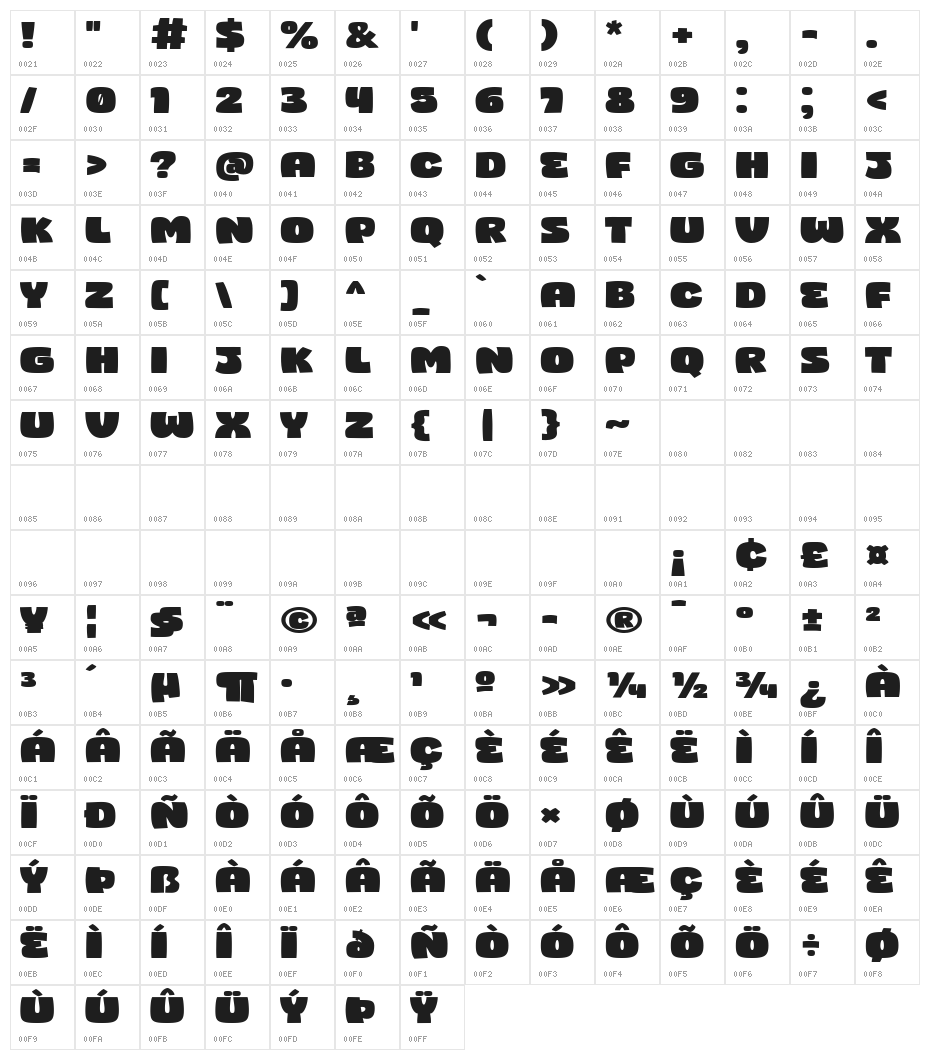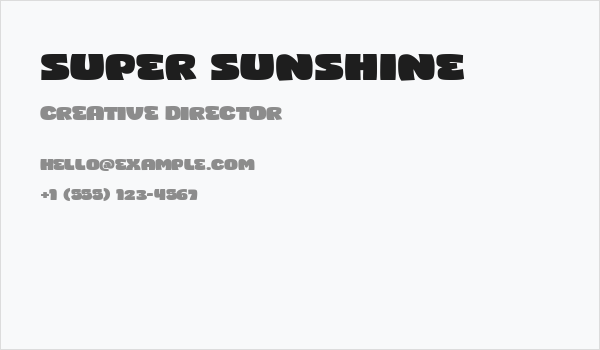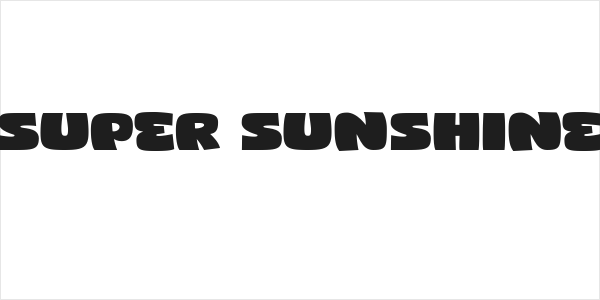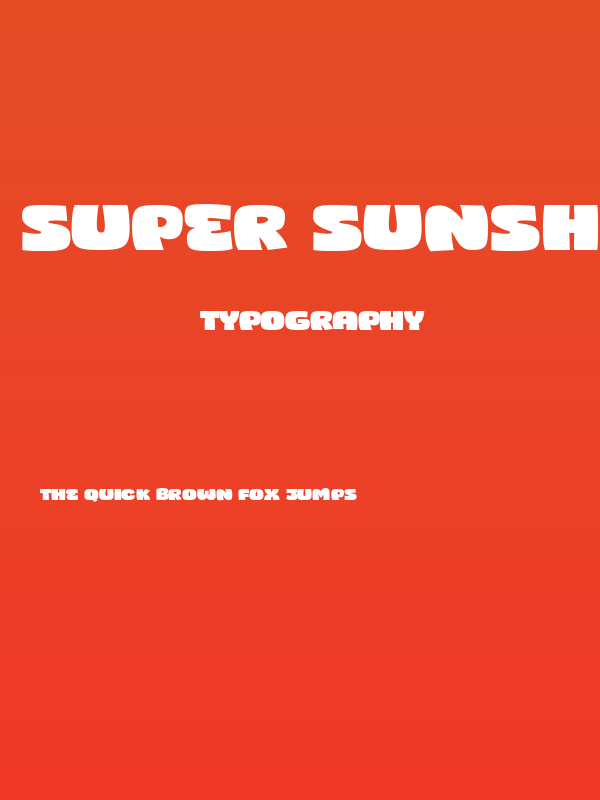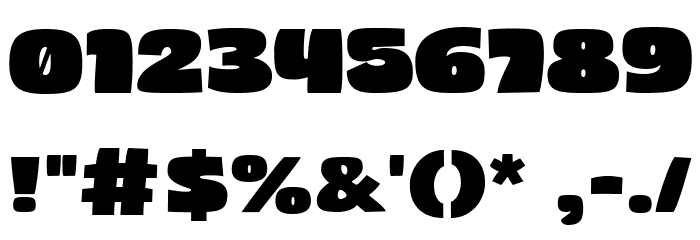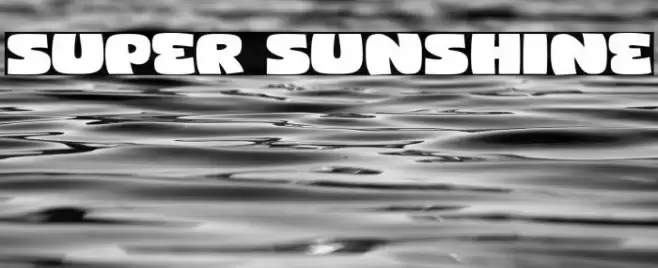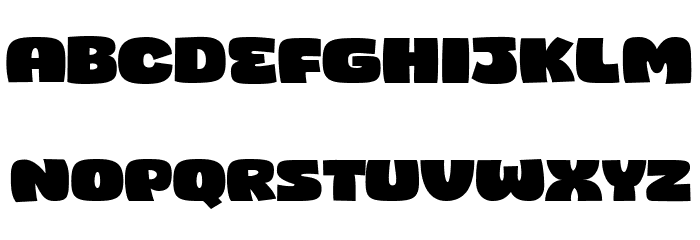
Super Sunshine Font
| العرض | Expanded |
| النمط العام | Playful, Fun, Whimsical |
| مشاريع مقترحة | Ideal for children's books, playful branding, posters, and any design needing a fun, engaging look. |